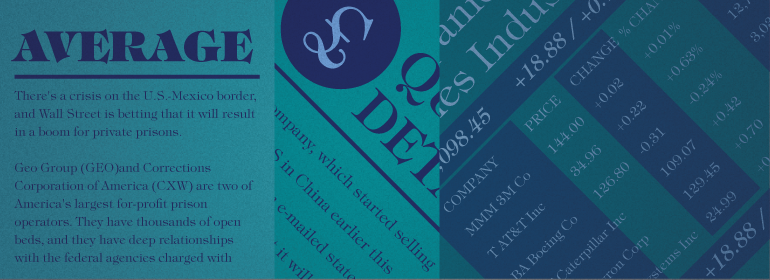
ITC Tiffany™
ITC Tiffany™,这款字体结构工整、笔画清晰,兼顾美观与易读性,适用于标题、正文、海报、包装、LOGO 等多种场景。字形优雅稳定,风格百搭耐看,适配日常排版与创意设计,让文字呈现更舒适、更具质感。ITC Tiffany™一笔一画,皆是细节,以均衡的比例、流畅的线条打造舒适视觉体验,字形端正大气,风格简约现代。无论是商业设计、品牌宣传还是日常排版,都能轻松驾驭,让文字更有格调与力量。ITC Tiffany™字体下载。
字体品牌: ITC(Monotype) 设计师:Benguiat,Edward 字体分类:衬线体 字体属性:外文 字符集:Unicode 发布时间: 2018
ITC Tiffany字体由Edward Benguiat设计,是Ronaldson与Caxton这两种字体的高度混合体。两者的最佳特点相结合产生了一种精致而清新的字体,ITC Tiffany。
ITC Tiffany font was designed by Edward Benguiat, a highly contemporary blend of two fonts, Ronaldson and Caxton. The best characteristics of both were combined to produce a refined and refreshing font, ITC Tiffany.